Phông chữ mảnh giống như chiếc ghế sofa tối giản đang "trendy" – nhìn thì sang chảnh trên ảnh, nhưng ngồi vào thì thật sự là thảm họa. Các nhà thiết kế đã bị ám ảnh bởi chúng suốt nhiều năm, xem đó như biểu tượng của sự tinh tế, sang trọng và đẳng cấp thương hiệu. Nhưng hãy thực tế một chút: phông chữ mảnh là một thảm họa về khả năng sử dụng và tiếp cận.
Chúng khiến mắt mỏi, biến mất trên một số màn hình, và hoàn toàn xa lánh những người không có thị lực hoàn hảo. Thế nhưng trong nhiều năm qua, các thương hiệu và nhà thiết kế vẫn cố chấp, bắt người dùng phải nheo mắt nhìn vào những dòng chữ mờ ảo chỉ để đọc một menu hay nút kêu gọi hành động. Thật là bức bối, nhưng tin tốt là: một số nhà thiết kế cuối cùng cũng đã tỉnh ngộ.
Ngày càng nhiều website âm thầm từ bỏ kiểu chữ siêu mảnh để chuyển sang loại chữ mà người dùng có thể thực sự đọc được. Ví dụ, Apple từng "ép" kiểu chữ mảnh vào iOS 7, nhưng sau đó đã phải lùi bước và tăng độ dày vì người dùng phàn nàn. Google cũng từng sử dụng Roboto Thin rất mảnh, nhưng rồi chuyển sang kiểu chữ rõ ràng và dễ nhìn hơn.
Ngay cả những thương hiệu từng tự hào với phong cách siêu tinh tế—như các hãng thời trang cao cấp—giờ cũng đang ưu tiên khả năng đọc hơn là sự "bóng bẩy".
Vậy tại sao lại mất quá nhiều thời gian mới nhận ra?
Cơn sốt phông chữ mảnh thực sự bùng nổ cùng với làn sóng tối giản. Khoảng trắng, xám nhạt, và chữ gần như "vô hình" trở thành tiêu chuẩn của cái gọi là “hiện đại” và “cao cấp”.
Roboto Thin của Google
Và đúng là nhìn rất đẹp trong môi trường lý tưởng – màn hình độ phân giải cao, ánh sáng hoàn hảo, bạn ngồi thoải mái và không thực sự phải sử dụng website. Nhưng khi bước vào thực tế – ánh sáng kém, màn hình nhỏ, mắt kém – phông chữ mảnh biến thành ác mộng.
Và đừng nghĩ đây chỉ là chuyện thẩm mỹ. Nhiều thương hiệu dùng phông mảnh như một biểu tượng đẳng cấp. Chúng không được tạo ra để dễ đọc – mà để thể hiện sự độc quyền. Nếu bạn không đọc được? Có lẽ bạn không phải "đối tượng phù hợp".
Không lạ khi cả những công ty như Google – từng ủng hộ phông siêu mảnh – cũng đã đổi hướng. Các phiên bản sau của Material Design chuyển sang kiểu chữ đậm hơn, dễ đọc hơn, vì họ nhận ra: người dùng cần thấy rõ chữ.
Xem Spotify mà xem. Ứng dụng đầu tiên của họ dùng chữ mảnh đến mức khó đọc khi bạn đang đi bộ hay trên xe. Theo thời gian, họ chuyển sang phông đậm hơn với độ tương phản cao. Ngay cả Instagram – từng là biểu tượng của thiết kế siêu mảnh – cũng đã điều chỉnh phông chữ để dễ đọc hơn.
Các thương hiệu cao cấp cũng bắt đầu hiểu ra. Một số nhà bán lẻ thời trang cao cấp đã bỏ những kiểu chữ mỏng dính để chuyển sang thứ có thể đọc được bằng mắt người – nghe có vẻ “cách mạng” ghê!
Không chỉ các tên tuổi lớn. Nhiều thương hiệu nhỏ và startup cũng nhận ra rằng: dễ đọc = giữ chân người dùng. Những website ưu tiên trải nghiệm – như báo chí, thương mại điện tử, hay mạng xã hội – đang hướng tới kiểu chữ dày, đậm và dễ đọc hơn.
Vậy nhà thiết kế nên làm gì?
Trước hết, ngừng mặc định chọn phông mảnh. Một kiểu chữ nhìn đẹp trong bản mockup tĩnh không có nghĩa là sẽ dùng tốt trong thực tế.
Thứ hai, hãy kiểm tra kiểu chữ trong các điều kiện khác nhau. Dùng thử trên điện thoại, trên màn hình khác nhau, dưới ánh sáng khác nhau. Nếu bạn không đọc nổi, người khác cũng vậy.
Thứ ba, hãy tăng độ tương phản. Chữ xám nhạt trên nền trắng nhìn có vẻ hiện đại, nhưng là thảm họa về trải nghiệm. Hãy làm cho văn bản nổi bật – người dùng sẽ biết ơn bạn.
Và cuối cùng, hãy phản biện lại quyết định sai của khách hàng. Nếu khách hàng nhất quyết chọn phông siêu mảnh vì nghĩ nó “cao cấp”, hãy đưa ra số liệu. Giải thích vì sao trải nghiệm và khả năng tiếp cận ảnh hưởng trực tiếp đến tương tác. Nếu họ vẫn muốn tự phá website của mình, ít nhất bạn đã cố gắng.
Thiết kế tốt không chỉ là đẹp – mà còn phải có chức năng. Kiểu chữ tốt không chỉ thì thầm – nó phải nói to và rõ ràng.
Vậy nên, các nhà thiết kế: hãy ngừng khiến người dùng phải chịu đựng. Hãy chọn kiểu chữ dễ đọc. Hãy làm cho nội dung dễ tiếp cận. Và vì tất cả những gì tốt đẹp của UX, hãy để phông chữ mảnh yên nghỉ.
Chúng khiến mắt mỏi, biến mất trên một số màn hình, và hoàn toàn xa lánh những người không có thị lực hoàn hảo. Thế nhưng trong nhiều năm qua, các thương hiệu và nhà thiết kế vẫn cố chấp, bắt người dùng phải nheo mắt nhìn vào những dòng chữ mờ ảo chỉ để đọc một menu hay nút kêu gọi hành động. Thật là bức bối, nhưng tin tốt là: một số nhà thiết kế cuối cùng cũng đã tỉnh ngộ.
Ngày càng nhiều website âm thầm từ bỏ kiểu chữ siêu mảnh để chuyển sang loại chữ mà người dùng có thể thực sự đọc được. Ví dụ, Apple từng "ép" kiểu chữ mảnh vào iOS 7, nhưng sau đó đã phải lùi bước và tăng độ dày vì người dùng phàn nàn. Google cũng từng sử dụng Roboto Thin rất mảnh, nhưng rồi chuyển sang kiểu chữ rõ ràng và dễ nhìn hơn.
Ngay cả những thương hiệu từng tự hào với phong cách siêu tinh tế—như các hãng thời trang cao cấp—giờ cũng đang ưu tiên khả năng đọc hơn là sự "bóng bẩy".
Vậy tại sao lại mất quá nhiều thời gian mới nhận ra?
Tôn Thờ Thẩm Mỹ Hơn Chức Năng
Xu hướng thiết kế thật kỳ lạ. Một lúc thì ai cũng mê skeuomorphism, làm giao diện kỹ thuật số trông như sổ tay da hay kệ sách gỗ. Rồi bỗng dưng, tất cả được "dọn sạch", làm phẳng nút, và giảm phông chữ xuống chỉ còn nét mảnh như sợi tóc.Cơn sốt phông chữ mảnh thực sự bùng nổ cùng với làn sóng tối giản. Khoảng trắng, xám nhạt, và chữ gần như "vô hình" trở thành tiêu chuẩn của cái gọi là “hiện đại” và “cao cấp”.
Roboto Thin của Google
Và đúng là nhìn rất đẹp trong môi trường lý tưởng – màn hình độ phân giải cao, ánh sáng hoàn hảo, bạn ngồi thoải mái và không thực sự phải sử dụng website. Nhưng khi bước vào thực tế – ánh sáng kém, màn hình nhỏ, mắt kém – phông chữ mảnh biến thành ác mộng.
Và đừng nghĩ đây chỉ là chuyện thẩm mỹ. Nhiều thương hiệu dùng phông mảnh như một biểu tượng đẳng cấp. Chúng không được tạo ra để dễ đọc – mà để thể hiện sự độc quyền. Nếu bạn không đọc được? Có lẽ bạn không phải "đối tượng phù hợp".
Thảm Họa Về Khả Năng Tiếp Cận Mà Ai Cũng Phớt Lờ
Rõ ràng đây không chỉ là phiền toái – mà là một rào cản thực sự đối với hàng triệu người. Người có thị lực yếu, mù màu, hoặc khó khăn nhận thức gặp khó khăn khi đọc phông mảnh. Nhiều phông trong số này còn không vượt qua các bài kiểm tra tương phản cơ bản, nhất là khi kết hợp với những bảng màu "trendy" nhưng nhợt nhạt.Trải Nghiệm Trên Di Động Còn Tệ Hơn
Nếu phông mảnh tệ trên desktop, thì trên di động là thảm họa. Màn hình nhỏ khiến chữ vốn đã mảnh lại càng khó đọc. Cộng thêm ánh sáng chói, môi trường thiếu sáng, hoặc tay run khi đang cuộn – phông chữ “thanh lịch” của bạn bỗng trở nên hoàn toàn không đọc nổi.Không lạ khi cả những công ty như Google – từng ủng hộ phông siêu mảnh – cũng đã đổi hướng. Các phiên bản sau của Material Design chuyển sang kiểu chữ đậm hơn, dễ đọc hơn, vì họ nhận ra: người dùng cần thấy rõ chữ.
Cái Chết Từ Từ Của Phông Mảnh (Và Vì Sao Các Website Đang Dần Thay Đổi)
May mắn là chúng ta đang thấy sự thay đổi. Những ông lớn như Apple, Google, Microsoft đã dần tăng độ dày phông chữ trong thiết kế giao diện. Ngành công nghiệp đang tỉnh ra rằng: trải nghiệm người dùng quan trọng hơn vẻ “ngầu”.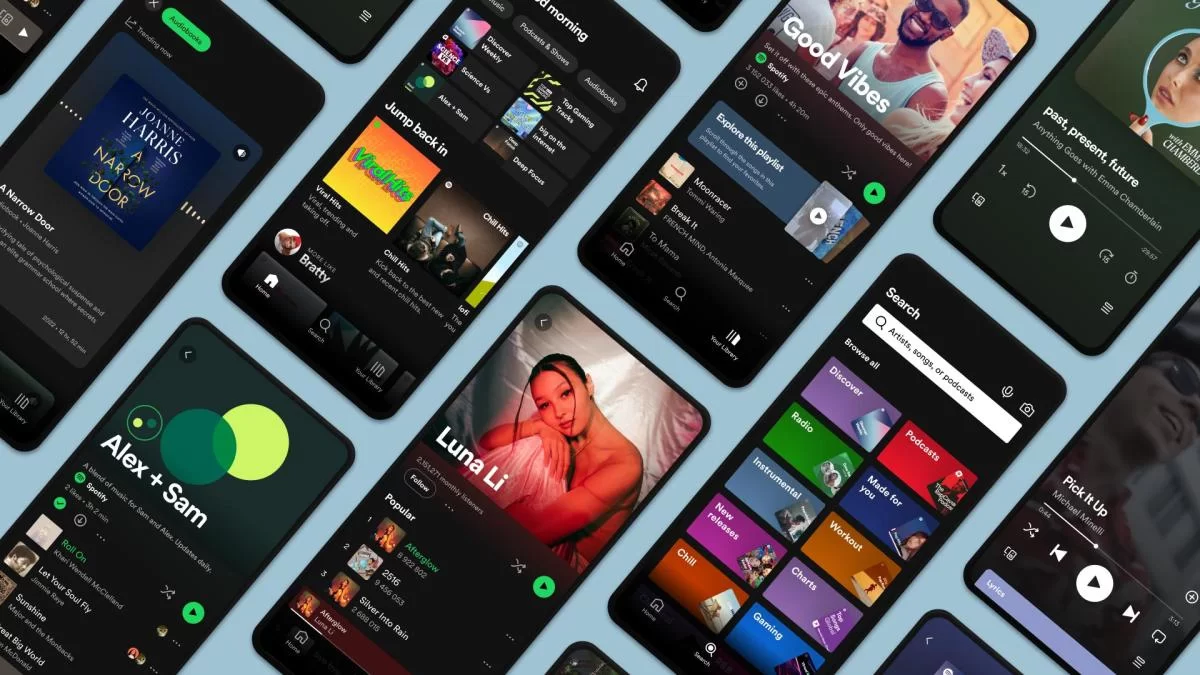
Xem Spotify mà xem. Ứng dụng đầu tiên của họ dùng chữ mảnh đến mức khó đọc khi bạn đang đi bộ hay trên xe. Theo thời gian, họ chuyển sang phông đậm hơn với độ tương phản cao. Ngay cả Instagram – từng là biểu tượng của thiết kế siêu mảnh – cũng đã điều chỉnh phông chữ để dễ đọc hơn.
Các thương hiệu cao cấp cũng bắt đầu hiểu ra. Một số nhà bán lẻ thời trang cao cấp đã bỏ những kiểu chữ mỏng dính để chuyển sang thứ có thể đọc được bằng mắt người – nghe có vẻ “cách mạng” ghê!
Không chỉ các tên tuổi lớn. Nhiều thương hiệu nhỏ và startup cũng nhận ra rằng: dễ đọc = giữ chân người dùng. Những website ưu tiên trải nghiệm – như báo chí, thương mại điện tử, hay mạng xã hội – đang hướng tới kiểu chữ dày, đậm và dễ đọc hơn.
Nhà Thiết Kế Cần Làm Gì (Và Nên Ngừng Gì)
Nói thẳng luôn: nếu bạn vẫn đang dùng phông siêu mảnh, bạn đang thiết kế cho quá khứ. Xu hướng này đang chết dần. Người dùng không muốn phải vất vả để đọc nội dung của bạn.Vậy nhà thiết kế nên làm gì?
Trước hết, ngừng mặc định chọn phông mảnh. Một kiểu chữ nhìn đẹp trong bản mockup tĩnh không có nghĩa là sẽ dùng tốt trong thực tế.
Thứ hai, hãy kiểm tra kiểu chữ trong các điều kiện khác nhau. Dùng thử trên điện thoại, trên màn hình khác nhau, dưới ánh sáng khác nhau. Nếu bạn không đọc nổi, người khác cũng vậy.
Thứ ba, hãy tăng độ tương phản. Chữ xám nhạt trên nền trắng nhìn có vẻ hiện đại, nhưng là thảm họa về trải nghiệm. Hãy làm cho văn bản nổi bật – người dùng sẽ biết ơn bạn.
Và cuối cùng, hãy phản biện lại quyết định sai của khách hàng. Nếu khách hàng nhất quyết chọn phông siêu mảnh vì nghĩ nó “cao cấp”, hãy đưa ra số liệu. Giải thích vì sao trải nghiệm và khả năng tiếp cận ảnh hưởng trực tiếp đến tương tác. Nếu họ vẫn muốn tự phá website của mình, ít nhất bạn đã cố gắng.
Lời Kết: Đã Đến Lúc Dừng Lại
Phông chữ mảnh là một sai lầm. Nhìn thì bóng bẩy một thời, nhưng chưa bao giờ thực tế. Giờ đây khi nhiều thương hiệu hướng tới kiểu chữ ưu tiên trải nghiệm người dùng, đã đến lúc bỏ lại quá khứ.Thiết kế tốt không chỉ là đẹp – mà còn phải có chức năng. Kiểu chữ tốt không chỉ thì thầm – nó phải nói to và rõ ràng.
Vậy nên, các nhà thiết kế: hãy ngừng khiến người dùng phải chịu đựng. Hãy chọn kiểu chữ dễ đọc. Hãy làm cho nội dung dễ tiếp cận. Và vì tất cả những gì tốt đẹp của UX, hãy để phông chữ mảnh yên nghỉ.